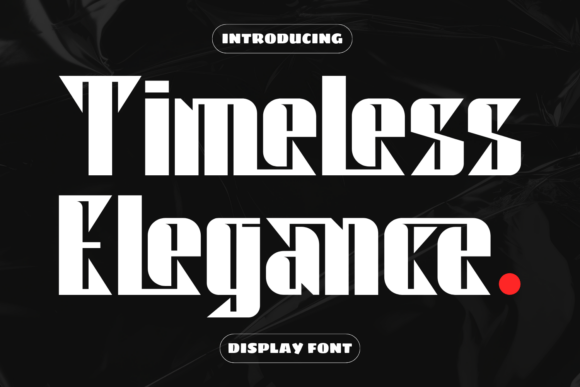
Timeless Elegance
Jika Anda mencari aset berkualitas tinggi seperti Timeless Elegance, paket premium ini adalah pilihan fantastis untuk proyek kreatif Anda.
Dibuat dengan presisi, Timeless Elegance menyediakan vektor yang bersih, tipografi yang halus, serta lisensi komersial untuk ketenangan pikiran Anda.